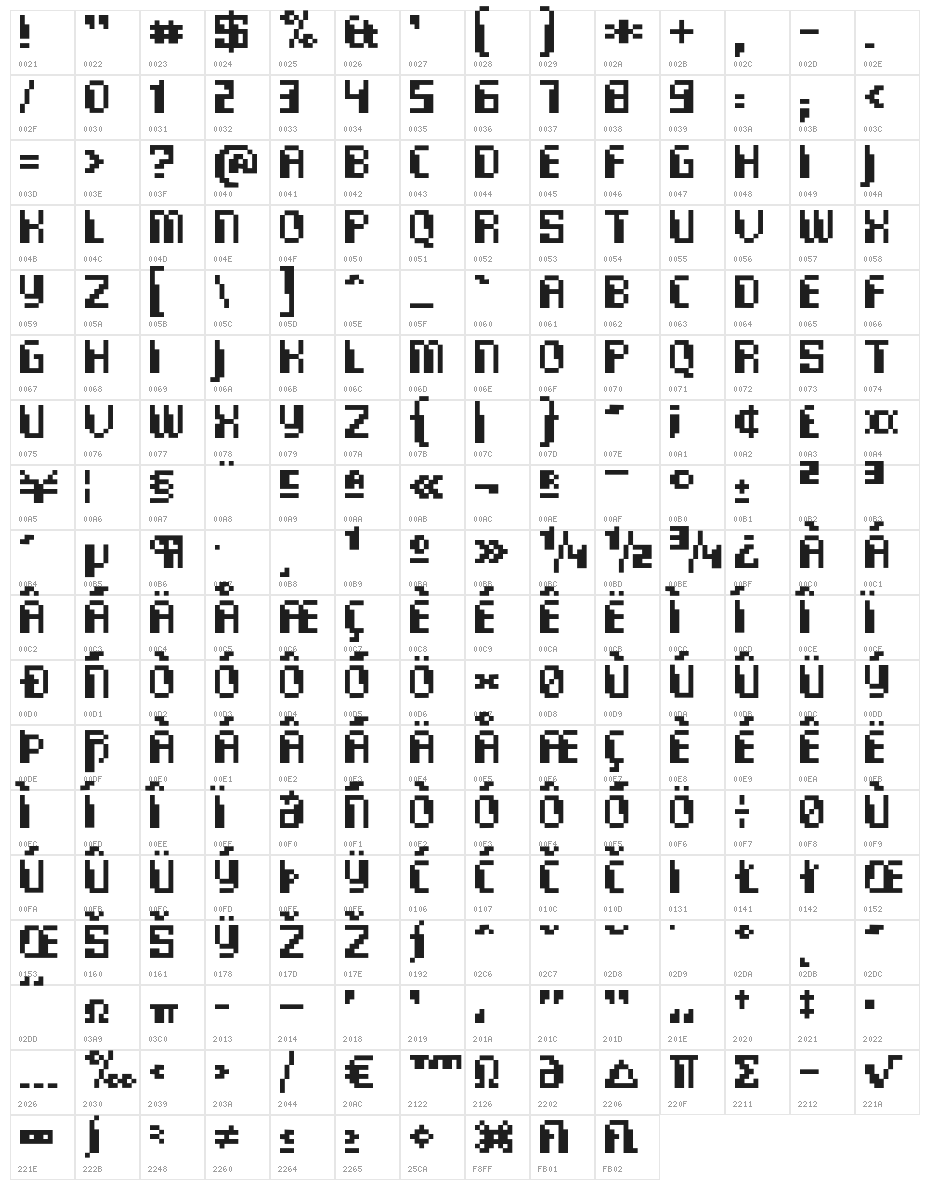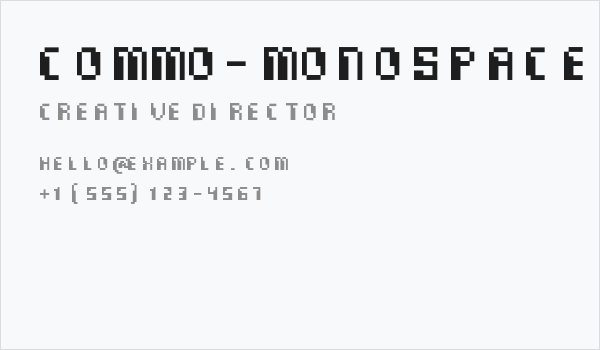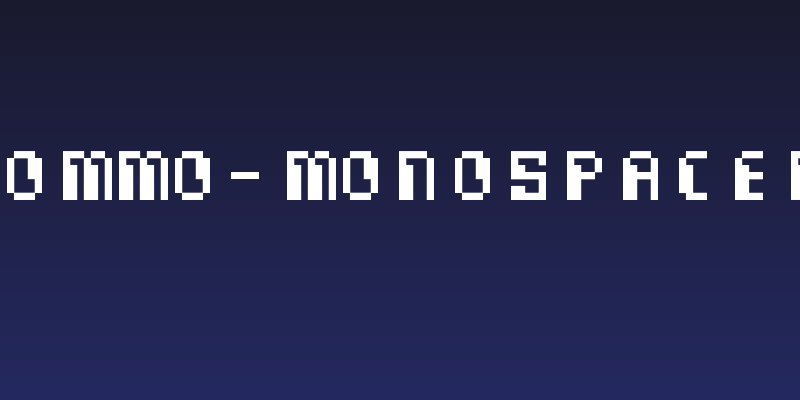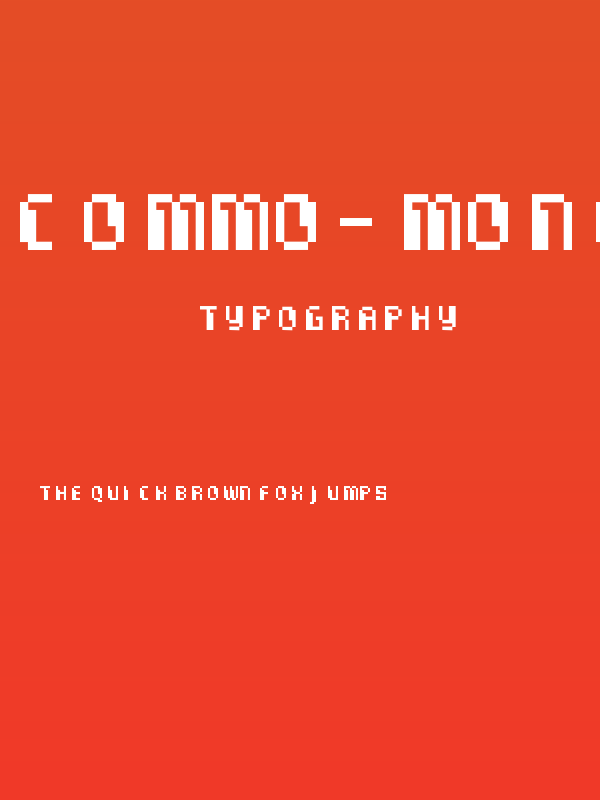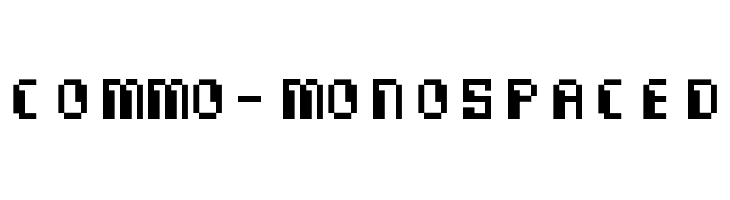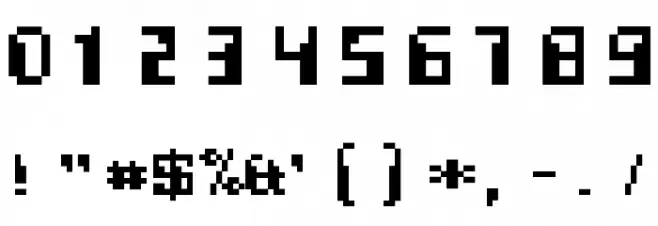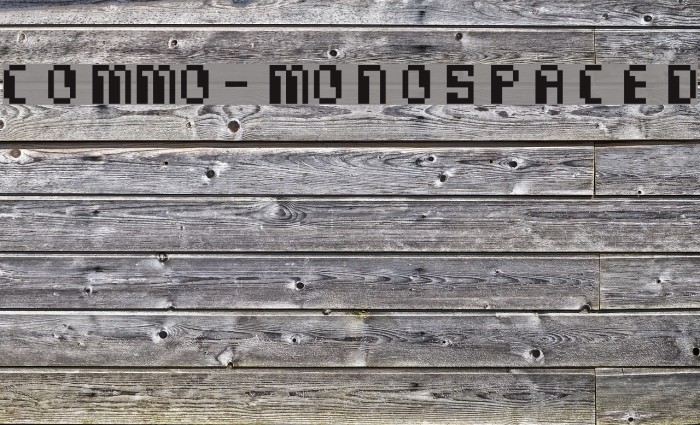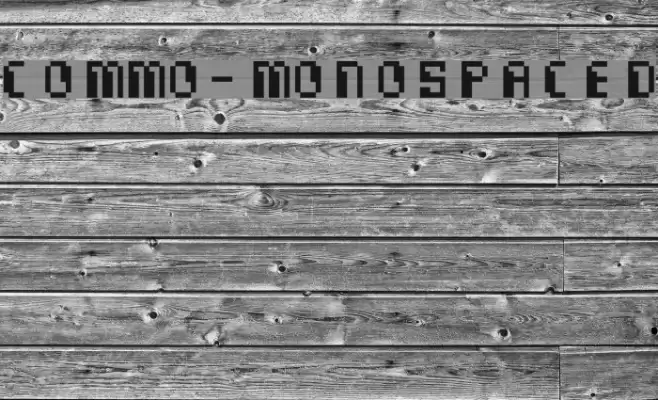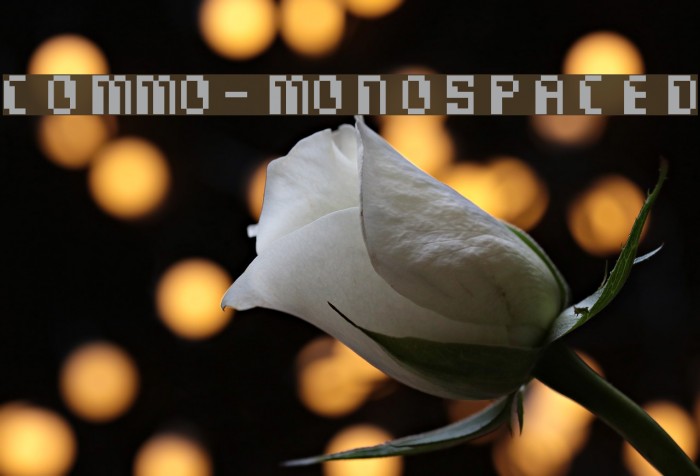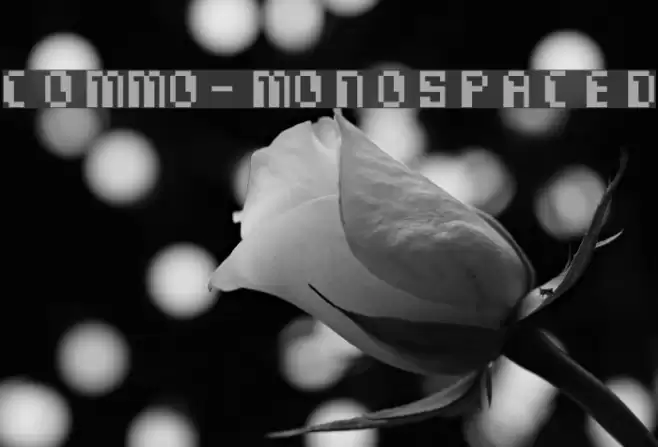
Commo-Monospaced Font
| Estilo general | Retro, Digital |
| Caso de uso | Coding, Digital displays, Retro designs |
| Proyectos propuestos | Ideal for coding environments, retro-themed designs, video game interfaces, or any project needing a digital or nostalgic aesthetic. |